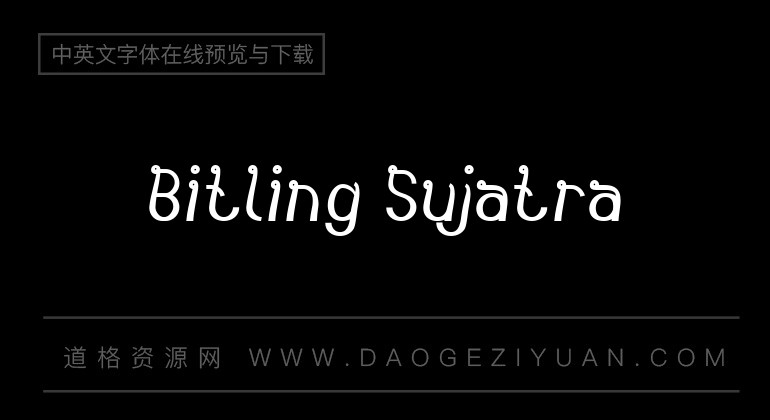
Bitling Sujatra
? Bitling Sujatra 是一款源自泰国的字体,它是一款宽字体,具有明显的曲线和折叠,特别适合用于标题和大型文本。它的字体风格非常精致,可以有效地增强文本的可读性,同时也可以给文本带来现代感。它的特点是拥有清晰的字形,同时又保留了传统的字体特色,使文本显得既传统又现代。
Bitling Sujatra是一款非常不错的手写艺术字体,具有很好的视觉感,适合于文化类的宣传设计、商业类品牌的广告和产品包装设计以及个性化文字排版等较多场景。